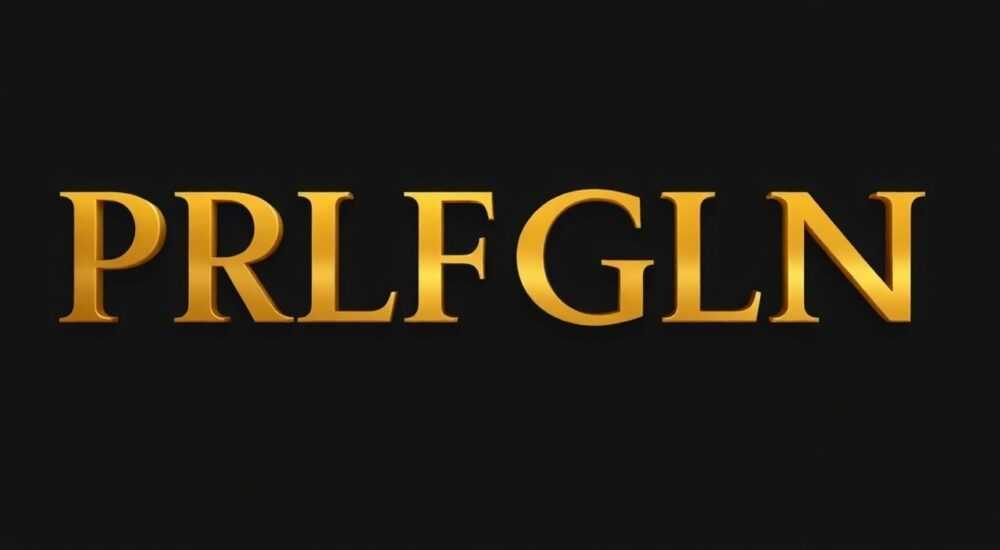
Как в фигме сделать золотой шрифт
Золотой шрифт в Figma — это стильный и эффектный способ выделить заголовки, логотипы или элементы премиум-дизайна. Он создаётся не через стандартные заливки, а с помощью градиентов, текстур и эффектов, имитирующих отражение света на металле. Ключевая рекомендация: используйте радиальный градиент с оттенками золота и добавьте эффекты свечения и тени для объёма.
Зачем нужен золотой шрифт в современном дизайне
Золотой шрифт давно перестал быть просто декоративным решением. Сегодня он активно используется в брендинге, рекламе, промо-материалах и интерфейсах премиальных продуктов. Такой типографика ассоциируется с роскошью, успехом и высоким качеством. Его применяют в логотипах ювелирных брендов, VIP-приглашениях, обложках музыкальных релизов и премиальных упаковках.
Использование золотого текста помогает сразу привлечь внимание пользователя. Исследования показывают, что глаз человека быстрее фиксирует блестящие и контрастные элементы. Золотистый цвет особенно эффективен при правильном сочетании с фоном — например, на тёмных или матовых поверхностях он «играет» светом и создаёт ощущение объёма.
При этом важно понимать: золотой шрифт — это не просто жёлтый цвет. Это сложная комбинация градиентов, отражений и текстур, имитирующих поведение настоящего металла под светом. Именно поэтому простая заливка одним цветом #FFD700 (классическое золото) редко даёт желаемый эффект.
Подготовка шрифта в Figma: выбор и настройка
Первый шаг к созданию золотого текста — правильный выбор шрифта. Не каждый тип шрифта подходит для имитации драгоценного металла. Оптимальными считаются шрифты с высокой контрастностью, толстыми засечками или плавными формами. Хорошие варианты: Playfair Display, Cinzel, Baskerville, Abril Fatface, Lobster.
Толщина начертания также важна. Для золотого эффекта лучше выбирать полужирные (Bold) или чёрные (Black) стили. Тонкие шрифты теряют объём и детализацию при наложении градиентов и эффектов. Размер текста должен быть достаточным — от 48px и выше, чтобы можно было разглядеть нюансы текстуры.
Перед началом работы преобразуйте текст в векторные фигуры. Это делается через Ctrl+Shift+O (или Layer → Outline Stroke). После этого вы сможете редактировать каждый контур, добавлять внутренние заливки и применять маски. Без этого шага невозможно добиться реалистичного рельефа.
- Выберите шрифт с выраженным характером и достаточной толщиной.
- Убедитесь, что текст легко читается даже после применения эффектов.
- Преобразуйте текст в векторы перед настройкой заливки и эффектов.
Направление света и композиция
Один из ключевых моментов — определение источника света. В реальности золото отражает свет, создавая блики и тени. Чтобы текст выглядел естественно, нужно задать угол падения света — обычно 45° сверху слева. Это повлияет на расположение градиентов и внутренних теней.
Если ваш макет содержит другие объёмные элементы, убедитесь, что направление света у них совпадает. Несоответствие сделает дизайн «плоским» и непрофессиональным. Используйте вспомогательные линии (guides), чтобы закрепить положение воображаемого источника света.
Создание градиентной заливки: основа золотого эффекта
Градиент — сердце золотого шрифта. Простая заливка одним цветом не передаст глубину и игру света. Нужно использовать линейный или радиальный градиент с несколькими точками останова, имитирующими переходы на поверхности металла.
Откройте панель заливки (Fill) и выберите Gradient Fill. Лучше начать с линейного градиента под углом 45°. Цветовые точки должны включать:
- Светло-золотой (#FFF1B3) — для бликов;
- Классическое золото (#FFD700);
- Тёмно-золотой (#C5A100) — для теней;
- При необходимости — коричневатый оттенок (#8B6F00) для глубины.
Регулируйте положение точек так, чтобы светлый участок был в верхней левой части буквы — это соответствует направлению света. Избегайте резких переходов: используйте сглаженные остановы (smooth stops), перемещая ползунки близко друг к другу.
Цвет |
HEX-код |
Назначение |
Светло-золотой |
#FFF1B3 |
Высветление, блик |
Классическое золото |
#FFD700 |
Основной цвет |
Тёмно-золотой |
#C5A100 |
Тень, объём |
Глубокий оттенок |
#8B6F00 |
Контраст, реалистичность |
Радиальный градиент для выпуклости
Для дополнительного объёма можно наложить второй слой — радиальный градиент. Создайте копию текста, поместите её под основной слой и примените радиальный градиент от белого к прозрачному. Установите режим наложения Overlay или Soft Light. Это создаст эффект выпуклости, как будто буквы слегка выступают.
Дополнительные эффекты для реализма
Чтобы золотой шрифт выглядел ещё более реалистично, добавьте эффекты из панели Effects. Особенно важны:
- Drop Shadow — тонкая тень снизу, создаёт ощущение парения над фоном.
- Inner Shadow — имитирует углубления и рельеф внутри букв.
- Glow / Outer Glow — мягкий ореол, усиливающий впечатление светящегося металла.
Настройте Drop Shadow: Y=2, Blur=4, Color=#00000020. Inner Shadow: Y=-1, Blur=2, Color=#00000040. Эти значения создадут лёгкий, но заметный объём. Для свечения используйте цвет #FFF9C4 с размытием 8–10px и низкой непрозрачностью.
Маски и многослойность
Для максимальной глубины используйте многослойный подход. Создайте три копии текста:
- Нижний слой — тёмный градиент (основа теней).
- Средний слой — основной золотой градиент.
- Верхний слой — маска с белым радиальным градиентом (блики).
Верхний слой установите в режим Screen или Linear Dodge, чтобы он пропускал только светлые участки. Это имитирует отражение света на полированной поверхности.
Работа с текстурами металлов и бликов
Для достижения максимального реализма можно добавить текстуру. В Figma поддерживаются изображения в качестве заливки. Найдите HD-текстуру золота (например, на сайтах вроде TextureNinja или Pixabay), загрузите её и примените как Image Fill к тексту.
Важно: используйте маску, чтобы текстура оставалась только внутри контуров букв. Активируйте Use as Mask на нижнем слое текста, затем поместите текстуру сверху и привяжите её.
Альтернатива — использование плагинов. Популярные решения:
- Metallic Text Generator — создаёт готовые металлические стили с одним кликом.
- Blush Gradient — помогает подбирать реалистичные градиенты, включая золото.
- Auto Shadows — автоматически рассчитывает тени по направлению света.
Ошибки, которых стоит избегать
Даже опытные дизайнеры иногда допускают типичные ошибки при создании золотого текста. Вот основные из них:
- Слишком яркие цвета — чисто жёлтый или оранжевый текст выглядит дешево. Золото всегда имеет теплые, слегка грязноватые оттенки.
- Отсутствие теней и бликов — плоский градиент без объёма не воспринимается как металл.
- Несоответствие стилю проекта — золото уместно не везде. В минималистичных или tech-интерфейсах оно может выглядеть чужеродно.
- Перегрузка эффектами — слишком много свечения, теней и текстур делает текст нечитаемым.
Как проверить качество
Перед финализацией протестируйте текст:
- Посмотрите на него в чёрно-белом режиме (через grayscale filter). Контраст между бликами и тенями должен сохраняться.
- Уменьшите масштаб до 50%. Читаемость и эффект должны остаться.
- Проверьте на разных фонах: тёмном, светлом, текстурированном.
Экспорт результата: советы по сохранению качества
После завершения работы экспортируйте текст правильно. В зависимости от цели выбирайте формат:
- PNG с прозрачным фоном — для веба, презентаций, соцсетей. Выберите разрешение x2 или x3 для ретины.
- SVG — если нужно масштабировать без потерь. Убедитесь, что градиенты и эффекты корректно экспортируются (иногда SVG теряет сложные заливки).
- PDF — для печати. Подходит для VIP-материалов, где важна детализация.
Если вы передаёте макет разработчику, оставьте слои структурированными: называйте группы (например, «Text — Gold Main», «Effects — Inner Shadow»). Это упростит реализацию в коде или при анимации.
Создание золотого шрифта — это не просто техническая задача, а микс художественного чутья и знания поведения материалов. Профессионалы рекомендуют начинать с анализа референсов: фотографий ювелирных изделий, логотипов люксовых брендов, гравировки на металле.
Главный принцип — меньше правил, больше наблюдений. Смотрите, как свет падает на кольцо, как отражается в углублениях буквы, где находятся самые тёмные тени. Переносите эти закономерности в Figma.
Создание золотого шрифта в Figma — это искусство имитации материала с помощью цифровых инструментов. Успех зависит не от количества эффектов, а от понимания физики света и умения работать с градиентами, тенями и текстурами. Главное — сохранять баланс между красотой и читаемостью.
- Золотой шрифт строится на градиенте, а не на одном цвете.
- Объём достигается за счёт inner shadow, drop shadow и бликов.
- Направление света должно быть единым по всему макету.
- Текстуры и плагины ускоряют работу, но не заменяют базовые навыки.
- Экспорт в PNG или SVG с учётом контекста использования.